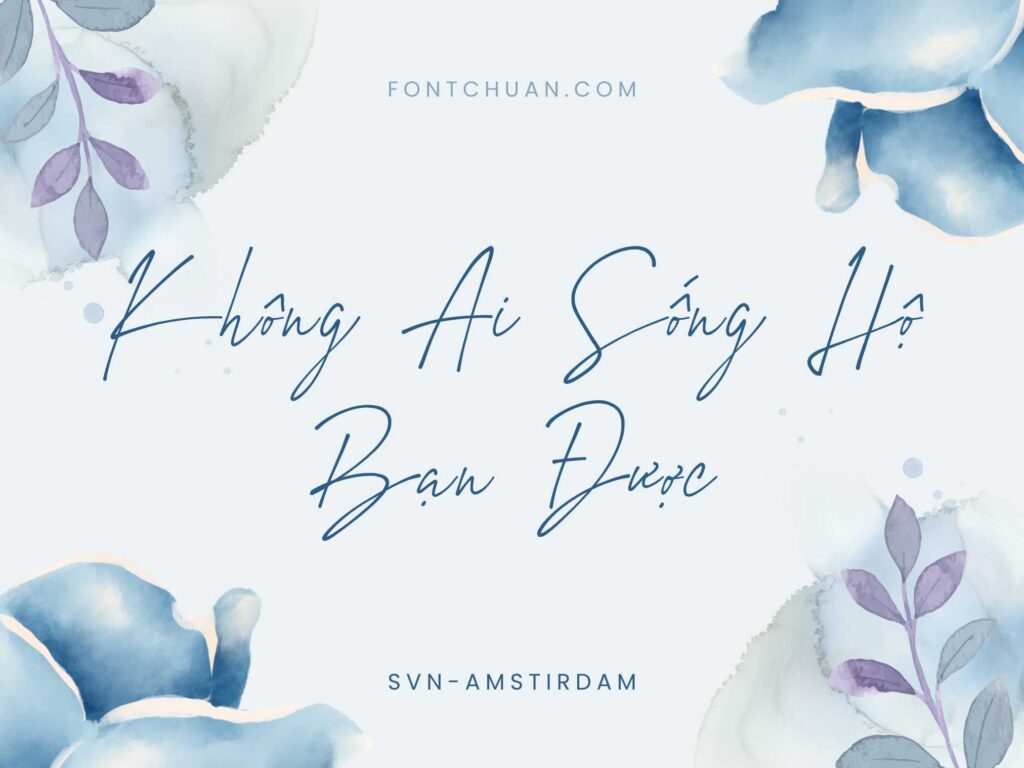
Font SVN Amstirdam Việt Hóa
Tác giả Font: Semuthitam Creative
Amstirdam là một font chữ viết tay thanh lịch, được thiết kế bởi Semuthitam. Font này mang phong cách hiện đại và tinh tế, phù hợp cho nhiều mục đích sử dụng như thiết kế logo, thiệp mời, tiêu đề, áo thun và các dự án sáng tạo khác. Với bộ ký tự đầy đủ bao gồm chữ hoa, chữ thường, số, dấu câu và các ligature, Amstirdam cung cấp sự linh hoạt cho các nhà thiết kế trong việc tạo ra những tác phẩm độc đáo. Font đã được Việt hóa để hỗ trợ tiếng Việt bởi Styleno.1 Fonts, đồng thời hỗ trợ nhiều ngôn ngữ khác, giúp mở rộng phạm vi sử dụng trên toàn cầu. Font này được thành viên của Font Chuẩn sưu tầm và chia sẻ, đáp ứng nhu cầu của bạn đọc và ứng dụng thực tế vào các dự án thiết kế.
Đặc điểm thiết kế của Amstirdam bao gồm các đường nét mềm mại, uyển chuyển và tự nhiên, tạo cảm giác như chữ viết tay thực sự. Font này phù hợp cho các ứng dụng như thiết kế thiệp mời, tiêu đề, logo, nhãn hiệu và các sản phẩm quảng cáo. Các ngành nghề phù hợp bao gồm quảng cáo, sự kiện, thời trang, làm đẹp và nghệ thuật.